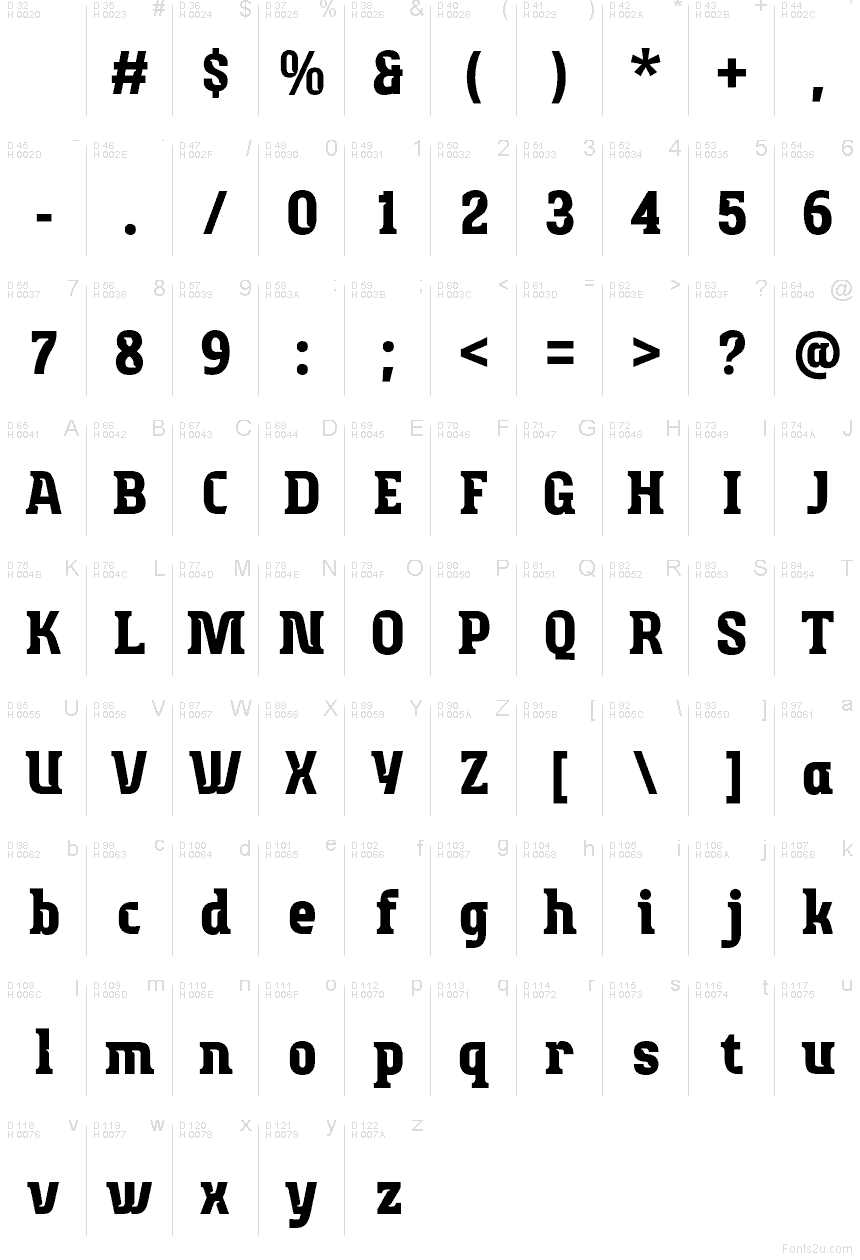
Runzoe es una fuente display gratuita de estilo slab-serif moderna de Afakari Studio, que combina letras robustas y geométricas con remates anchos y formas interiores suavemente redondeadas. Su marcado toque retro se percibe en las formas cuadradas repetidas y sus curvas compactas, otorgando al diseño una presencia sólida, ideal para cartelería.
Utiliza esta fuente gratuita para carteles de música, branding de cafeterías, etiquetas de productos, portadas editoriales y titulares de campañas. Sus formas densas y esculpidas son perfectas para rótulos y títulos, donde sus potentes remates pueden sostener la composición sin necesidad de adornos adicionales.